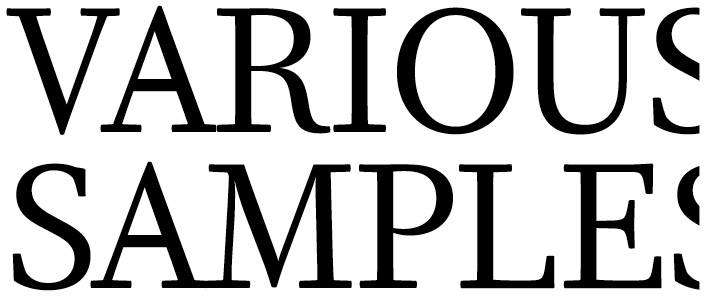
François Rappo von b + p schweizer schriften hat eine neue digitale Version von Pierre-Simon Fournier Schrift erstellt. Die Schrift besteht aus den Schnitten Regular, Regular Italic, Bold und Bold Italic. Jeden Schnitt gibt es in drei verschiedenen Designs: Book (optimiert für längere Texte), Big (optimiert für längere Texte; in Vergleich zum Book-Design detaillierter und mit historischer Anmutung) und Headline (optimiert für Titel). Darüberhinaus gibt es jeden dieser 3 × 4 Schnitte mit zwei unterschiedlichen Mittellängen. Insgesamt besteht die Schriftfamilie somit aus 2 × 3 × 4 = 24 Schnitten.
Joshua, hast Du die Typoart Fournier? Wenn ich bei Elsner+ Flake nachschaue, ist die Qualität der Bildschirmdarstellung so unbefriedigend, dass ich sie kaum zum Vergleich heranziehen kann … :-)
Danke, Pomeranz. In dem Vergleich sieht man meiner Meinung nach deutlich, daß die Typoart-Fassung ausgeglichener und gefälliger ist.
Und diese Kleckse in den runden Buchstaben (d, a) der Kursive sind auch sehr seltsam:
Die Typoart-Variante wirkt etwas weicher und freundlicher, das stimmt. :-) Und die Proportionen sind unterschiedlich, die x-Höhe bei der Typoart-Fournier ist kleiner, oder täuscht das? Spontan gefällt sie mir sehr gut, wobei ich mir vorstellen kann, dass die New Fournier auch ihre Anwendungsbereiche hat, in denen sie sich besser eignet als die Typoart-Schwester, sie wirkt etwas energischer. Bei der Kursiven hast Du recht, die tropfenförmigen Verbindungen beim »a« und beim »d« sind etwas seltsam.
wozu eine Schrift, die sich dazu noch auf historische Vorbilder beruft, zwei unterschiedliche Mittelhöhen braucht und hat. Um es mal mit Weidemann zu sagen: es kann doch eigentlich nur eine geben ... eine richtige.
Aber dann wäre es natürlich sinnvoll, der Schrift für kleine Grade nicht nur eine höhere Mittellänge sondern auch eine weitere Zurichtung zu geben. Das ist bei der New Fournier nicht geschehen. Ich denke eher, dass die verschiedenen x-Höhen für verschiedene Drucksachen (kleine x-Höhe für literarische Bücher; größere x-Höhe für Magazine) gedacht sind.
Ist doch ganz schick (für mich eher High Fashion, denn Leseschrift). Die etwas kitschige Strenge, das Aufwärtsstreben gefällt mir. Das Italic-a, -d ist vielleicht überkandidelt interpretiert worden …
Die Typoart-Variante ist mir zu weich, zu "transitional" – eine Fournier muss strenger sein, sonst könnte man gleich etwas anderes nehmen ;-)